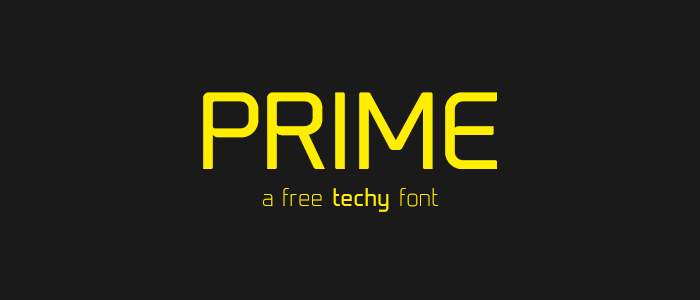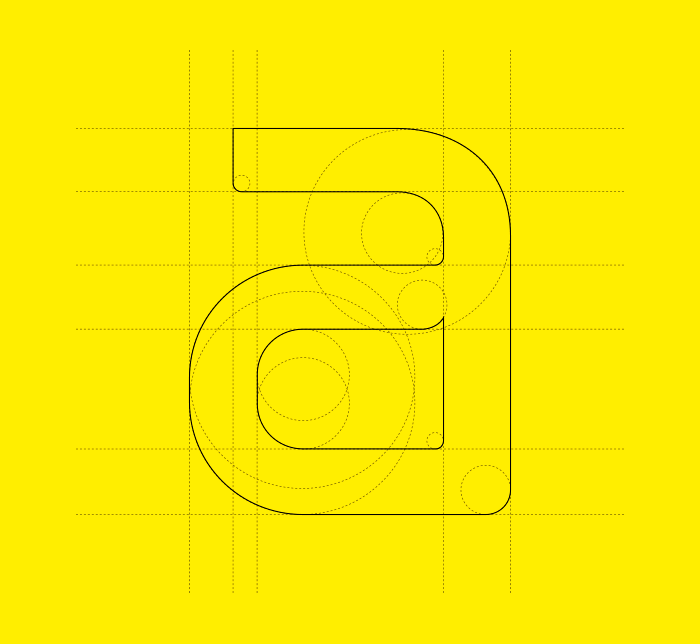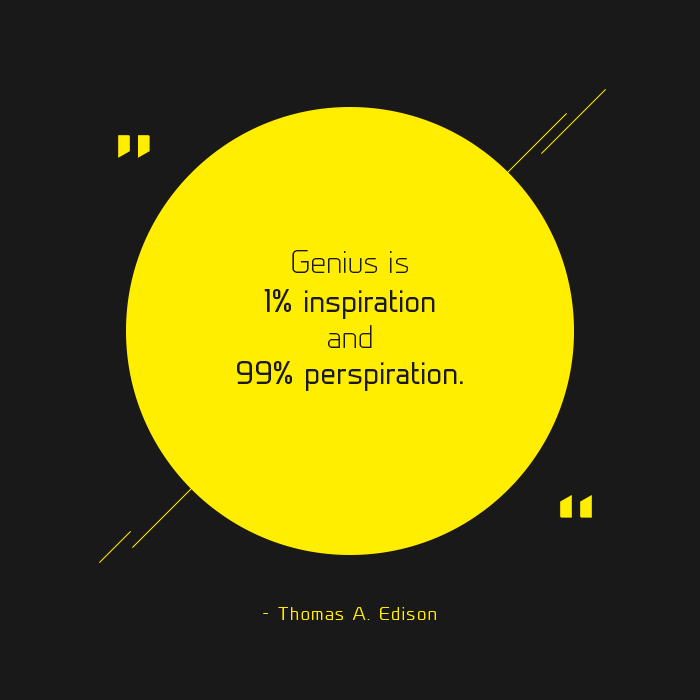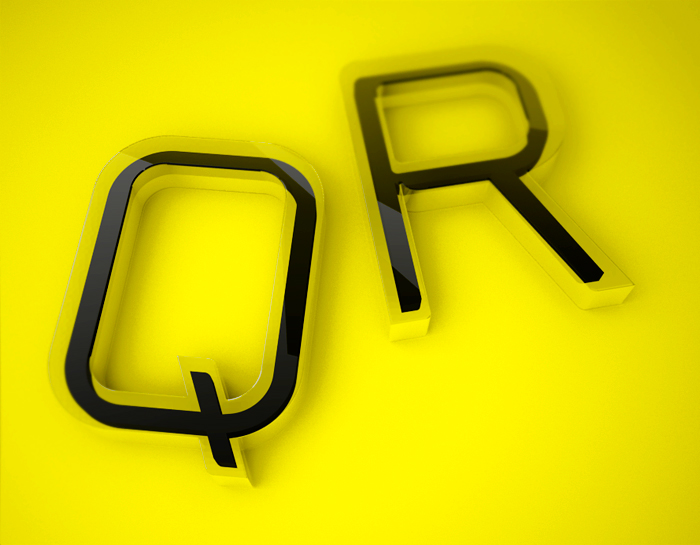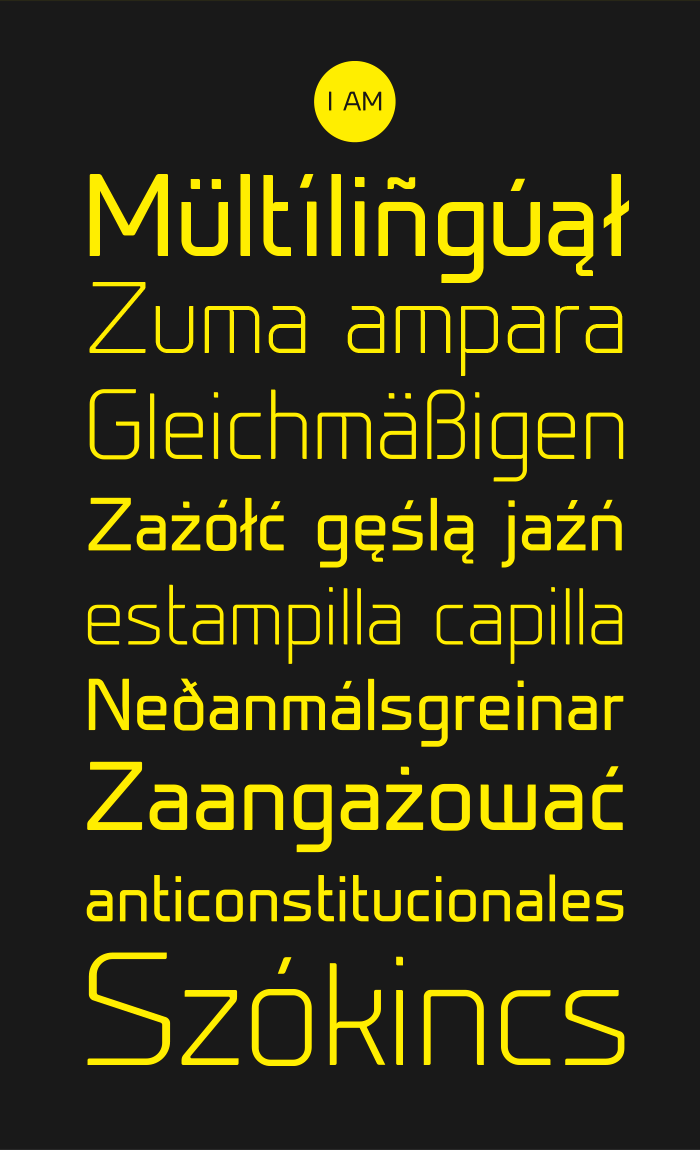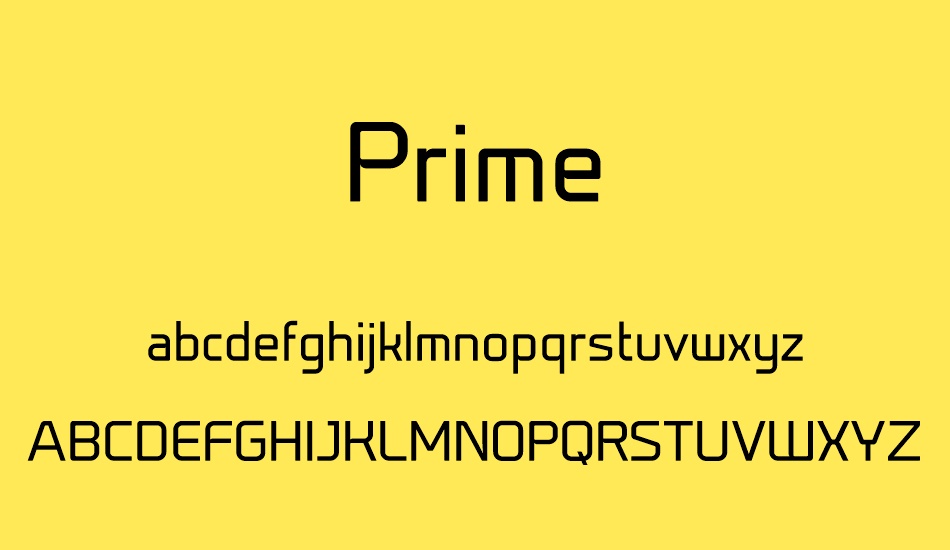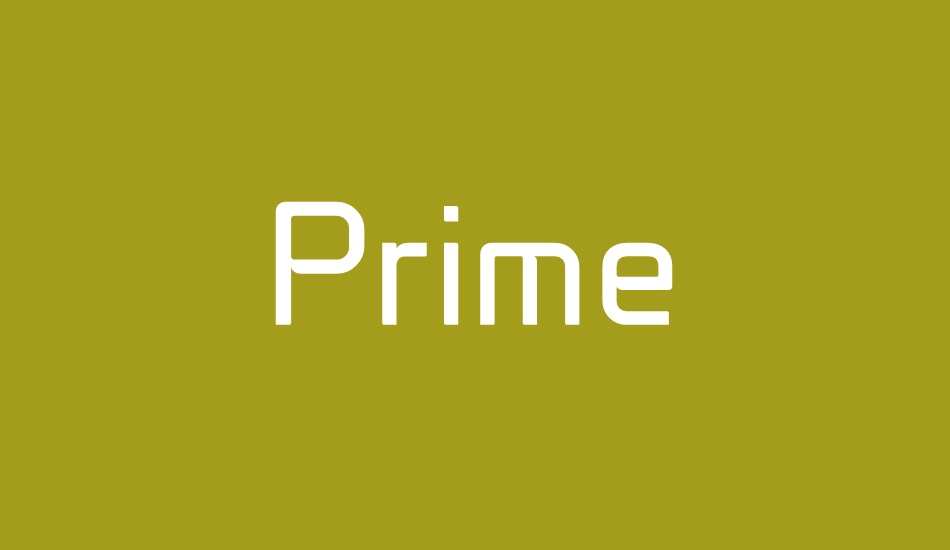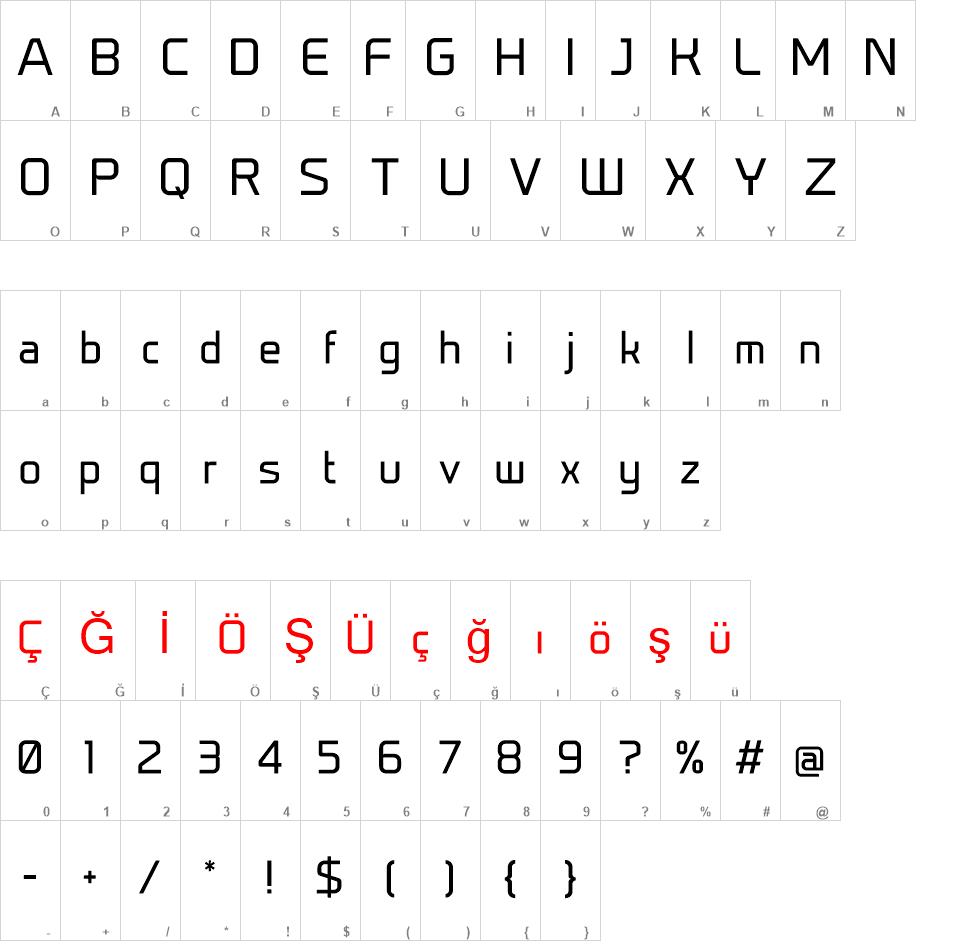
Prime, teknik bir hisse ve sıkı, geometrik bir orijine sahip basit bir yazı karakteridir. Çeşitli boyutlarda okunabilirliği yüksek, ancak göze çarpacak kadar ince farklılıklar sunan bir şeyler yaratmak istedim. Temel ve biraz nötr, farklı başlıklardan vücut metinlerine kadar çeşitli şekillerde kullanılabilir.
Prime font